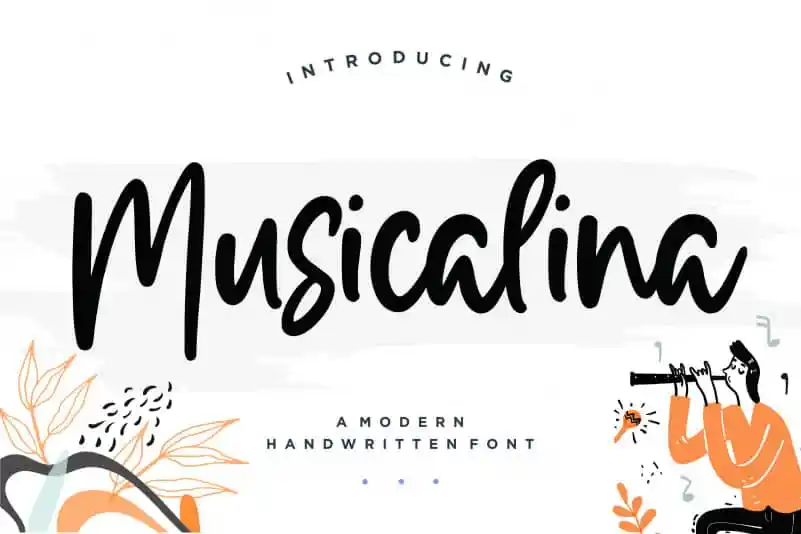
A Musicalina Modern Handwritten Font é uma fonte que traz alegria à qualquer projeto visual. Ela foi criada pelo talentoso designer balpirick e está perfeitamente adaptada para várias categorias de uso. Seja na criação de embalagens, identidade de marca ou até mesmo em projetos de revista ou redes sociais, a Musicalina Modern Handwritten fonte é uma escolha excelente. Com sua elegante escrita livre, essa fonte transmite um toque autêntico e criativo sem deixar de ser moderna. Ideal para expressar palavras acima de fundos coloridos em projetos de casamento ou simplesmente adicionar um ar pessoal a qualquer página, seja ela digital ou impressa. Seja você designer gráfico, editor de conteúdo ou até mesmo um influenciador digital, a Musicalina Modern Handwritten fonte tem o potencial de dar vida ao seu trabalho. Essa fonte é perfeita para quem busca uma opção que seja não apenas funcional e versátil, mas também capaz de destacar os detalhes com um toque único. Trazendo tanto profissionalismo quanto charme ao seu projeto, a Musicalina Modern Handwritten Font será o elemento definitivo que tornará sua arte visual destacadamente única.